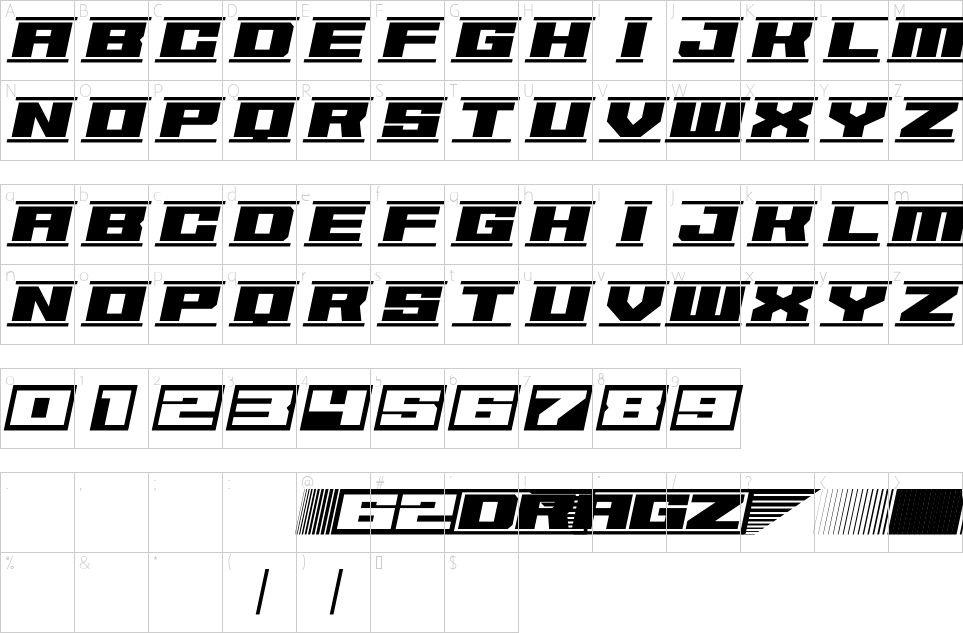
Aqui está uma breve descrição para a página de download da fonte ’62DRAGZ’, com foco no formato e na conveniência: Descubra 62DRAGZ, uma elegante fonte gratuita que você pode usar tanto em seu computador Windows quanto Mac. Esta fonte foi projetada por Youssef Habchi e já foi baixada mais de 39.978 vezes. Ideal para designers gráficos iniciantes e experientes, a ’62DRAGZ’ oferece um estilo moderno que se adaptará perfeitamente a vários tipos de projetos. Baixe agora a sua versão gratuita e adicione esse belo e fácil de usar estilo ao seu design. Seja para textos informativos ou artigos gráficos, 62DRAGZ vai manter o seu projeto impecável. Engajado e conveniente, é um presente para qualquer designer em busca de uma fonte moderna e versátil.